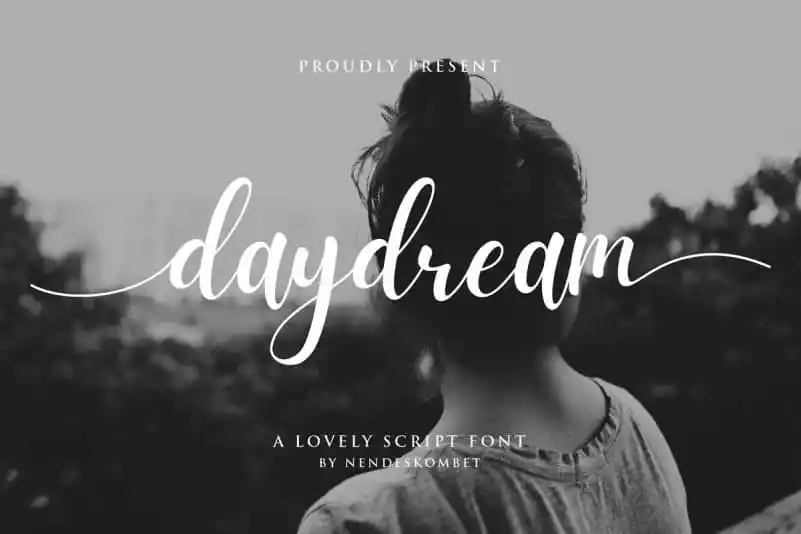
Daydream Calligraphy Font
A Daydream Calligraphy Font é uma escolha perfeita para quem quer adicionar um toque elegante ao seu design. Desenvolvida pelo designer 99designs, esta fonte de calligrafia moderna e chic possui alternativas de estilos florais sofisticadas que adicionam um ar sofisticado e único aos projetos. Suave e encantadoramente delicado, ela é perfeita para criações de casamento com o estilo de design minimalista em alta demanda. Seja você designer de gráficos, profissional ou amante da moda, a Daydream Calligraphy Font certamente fará seu trabalho: dar ao seu projeto um toque único e sofisticado. É uma escolha perfeita para designers em busca de uma fonte de calligrafia moderna que se destacará em qualquer design.